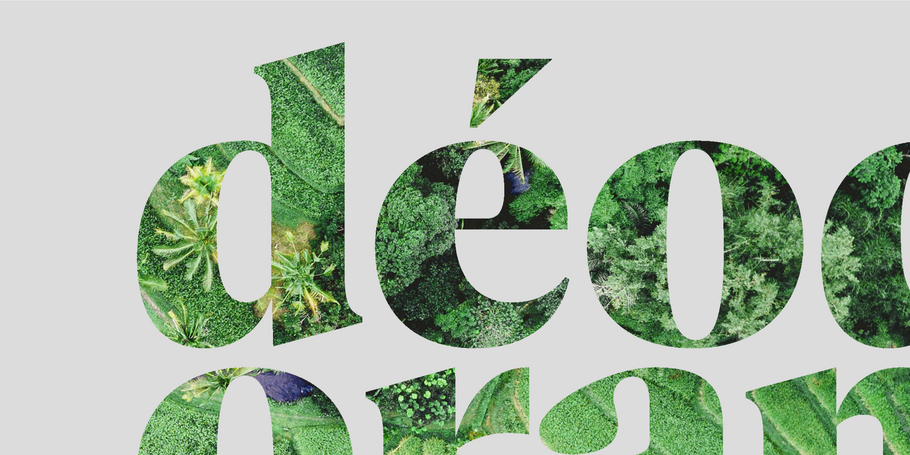
Alles kommt wieder: Warum wir uns nach Retro und Vintage sehnen.
Nostalgie, die den Menschen in Krisenzeiten ein gutes Gefühl gibt, hat gerade in allen Designdisziplinen Hochkonjunktur. Deshalb gehen wir der Frage nach, was diesen Trend antreibt und welche Probleme mit der Wiederbelebung historischer Designelemente verbunden sind.
In den letzten ein bis zwei Jahren hat sich in vielen Bereichen des täglichen Lebens eine Rückbesinnung breit gemacht: in Mode und bei Möbel, im Markendesign oder in der Musik, die wir streamen (Spotify: Top Throwbacks of 2021). In den beunruhigenden zwei Jahren, wie es viele von uns empfunden haben, war zu beobachten, dass Werbung und Design ein Gefühl der Geborgenheit schaffen wollten, indem sie das Vertraute neu erfanden. Die Wissenschaft bestätigt das. Psychologen haben herausgefunden, dass die Erinnerung an Vergangenes den Menschen dabei hilft, Krisen zu überstehen.
Wie Antiquitätensammler begeistern sich Designerinnen und Designer für historische Logos, alte Bücher, Poster und Plattencover. Sie zollen diesen Objekten Tribut, indem sie deren Ideen aufgreifen. Wie viele Schriften wurden in jüngerer Zeit durch Texte aus einem alten Buch inspiriert, auf das man in einem Antiquariat stieß, oder durch eine Postkarte, die man auf einem Flohmarkt erstand? Auf diese Art feiern wir Designikonen und Epochen, sei es in einem Logo, mit einem Plakat oder in unserem Zuhause.
Auch Monotypes jüngste Studio-Veröffentlichung, eine moderne Serif namens Cotford, entworfen vom Creative Type Director Tom Foley, hat einen nostalgischen Touch. „Cotford spiegelt eine Sehnsucht wider, die viele Menschen während des Höhepunkts der Lockdowns empfunden haben: die Sehnsucht nach Vertrautem und ein bisschen Wärme inmitten der Ungewissheit.“
Cotford from the Monotype Studio.
Der Nervenkitzel einer Entdeckung.
Außerhalb von Schrift- und Grafikdesign hat der Vintage-Stil in den Bereichen Möbel, Heimtextilien und Mode an Popularität gewonnen. Das Ritual, ein vergessenes Stück Geschichte wiederzuentdecken und ihm in der modernen Welt einen neuen Platz zu geben, sorgte in der Pandemie für Ablenkung und verbreitete sich über Social-Media-Kanäle genauso wie durch Secondhandshops à la Kleiderkreisel (seit November 2021: Vinted) oder Momox.
Modetrends waren schon immer zyklisch. Doch laut ThredUp, einem Online-Wiederverkäufer, hat sich der Gebraucht-Handel in den letzten Jahren zu einer 36-Milliarden-Dollar-Industrie entwickelt, die 2025 das Fast-Fashion-Business überholen könnte. Das Thema Nachhaltigkeit ist der Grund dafür, dass sich hauptsächlich jüngere Verbraucher für Secondhand statt für H&M entscheiden. Die Pandemie hat außerdem in fast allen Branchen zu Problemen bei der Lieferkette geführt, sodass viele Kunden die sofortige Befriedigung auf dem Trödelmarkt dem Warten auf einen verspäteten Versand von Neuware vorziehen.
Die Jagd nach Vintage-Perlen erstreckt sich auch auf die Welt des Wohnens, wie der Fotograf Tyler Haughey in unserem Podcast berichtete. In seiner Arbeit beschäftigt er sich mit visuellen Signalen, wie alte Schilder oder Ornamente, und untersucht, wie sie Erinnerungen oder Erfahrungen in unserem Gedächtnis verankern. „Die Erinnerungen sind anfangs sehr vertraut, nah und greifbar“, sagte Haughey. „Später dann, wenn man sich weiter entfernt, werden sie irgendwie seltsam und nehmen diesen Moment des Fantastischen an. Es liegt wohl im Wesen der Erinnerung, dass sie mit der Zeit immer unspezifischer wird.“
Alle diese Phänomene, ob gerundete Schriften im Stil der 70er-Jahre, weichgezeichnete Fotos untergegangener Strandmetropolen, ausrangierte Jeans oder antike Möbel, dienen als Auslöser für das Erzählen von Geschichten und die Wiederbelebung der Vergangenheit. In unserem Schrifttrend-Report 2021 haben wir erstmals den Trend der „Weichzeichner-Serif“ festgemacht, nachdem diese Art nostalgischer, Cooper Black-beeinflusster Schriften in den Rebrands von Chobani (InHouse), MailChimp (Collins), Meridian (BulletProof), Dunkin und Burger King (JKR) aufgetaucht sind. Nach einem weiteren Jahr der Pandemie zeigt sich dieser Trend immer noch stark, mit verspielten Schwüngen, abgerundeten Serifen, skurrilen Buchstaben und lebhafter Farbgebung.
JKR’s rebrand of Burger King.
Diversität historisch interpretieren
Schwierig wird es allerdings, wenn man die Wertschätzung für historische Designelemente von dem manchmal unangenehmen sozialen Kontext trennt, vor dem sie entstanden sind. In unserer Begeisterung für Nostalgie – gepaart mit einer rosaroten Brille – neigen wir dazu, die Rosinen herauszupicken und ignorieren Sexismus, Rassismus und soziale Ungleichheit. „Wir sagen einfach: ‚Ja, da gab es mal eine Zeit, in der weiße Männer Baseball spielen durften‘“, sagte Charles Nix, Creative Director bei Monotype, in einem Print Mag-Interview über die zu kurz gedachten Argumente zum Aufleben der Retro-Sporttrikots.
Um zurück auf. das Thema Schrift zu kommen … Tré Seals, Gründer und Inhaber von Vocal Type, setzt Schriften auch als Mittel zur Geschichtsbetrachtung ein. Alle Vocal-Schriften sind von historischen Ereignissen wie Demonstrationen und Protestbewegungen geprägt und nach prominenten Verfechtern für soziale Gerechtigkeit benannt, darunter Marsha P. Johnson, Martin Luther King und Bayard Rustin.
Vocal Type Work.
„Im März 2016, als ich ziellos durch Schriften scrollte, während ich eine neue visuelle Identität für eine Immobilienagentur entwarf, war ich einfach nur gelangweilt“, sagte Seals in einem Interview auf It’s Nice That. „Alles, was ich sah, egal wie gut, sah gleich aus. Man könnte argumentieren, dass es an der Obsession für Raster und Perfektion liegt. Aber die Wahrheit ist, dass keine Kultur, kein Charakter zu erkennen war … nur Monotonie und Stereotypen. Obwohl Design meine Leidenschaft ist, begann ich mich zu fragen, ob ich den falschen Beruf gewählt hatte.“